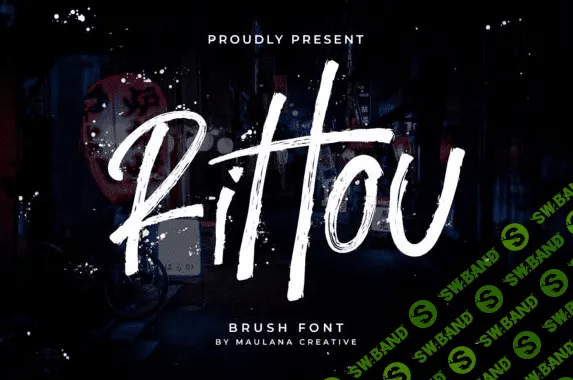
Название: Rittou Font
[Creativefabrica] Rittou Font
Придайте вашим дизайнам подлинное ощущение кисти ручной работы. "Rittou Brush Font" идеально подходит для подписи, канцелярских принадлежностей, логотипа, типографских цитат, обложки журнала или книги, заголовка веб-сайта, флаера, одежды, брендинга, дизайна упаковки и многого другого.